[Tải Xuống] Top 14+ Font Chữ Hoạt Hình Việt Hóa Đáng Yêu Và Vui Nhộn Cho 2025
Bài viết này tổng hợp 14+ font hoạt hình Việt hóa đẹp nhất năm 2025 – ngộ nghĩnh, dễ dùng và hiển thị hoàn hảo tiếng Việt.
Khi thiết kế dành cho trẻ em hoặc các sản phẩm mang hơi hướng vui nhộn, tươi sáng, font chữ hoạt hình luôn là sự lựa chọn khiến người xem bật cười ngay từ ánh nhìn đầu tiên. Không chỉ giúp truyền tải cảm xúc tích cực, những kiểu chữ này còn tạo nên cá tính riêng cho từng thiết kế – từ poster sinh nhật, sách tô màu, ứng dụng học tiếng Việt, đến sticker dán tường hoặc video trên YouTube.
1. Font chữ hoạt hình là gì?
Font chữ hoạt hình (hay cartoon font Việt hóa) là những kiểu chữ được thiết kế ngộ nghĩnh, vui tươi, thường mang hình khối tròn trịa, mềm mại hoặc phá cách. Chúng được lấy cảm hứng từ thế giới hoạt hình, truyện tranh hoặc các sản phẩm dành riêng cho trẻ em. Mỗi ký tự như đang “nhảy múa”, khiến thiết kế trở nên sinh động và gần gũi hơn bao giờ hết.
Không giống các font comic hay font script thông thường, font cartoon Việt hóa thường có đường nét dày dặn, bo cong kỹ lưỡng và thể hiện cá tính rất rõ – lý tưởng cho các nội dung cần thu hút ánh nhìn và lan tỏa sự vui nhộn.
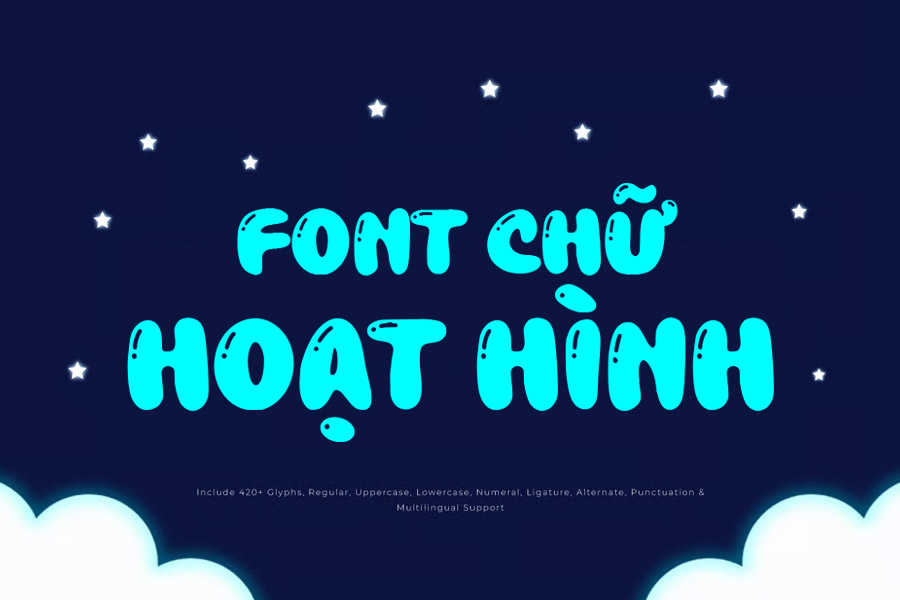
2. Vì sao nên chọn font hoạt hình Việt hóa?
Sử dụng các font hoạt hình Việt hóa giúp bạn:
- Tránh lỗi hiển thị dấu tiếng Việt – nhất là trên Canva, PowerPoint, hoặc khi in ấn.
- Dễ dàng dùng trên mọi nền tảng thiết kế – kể cả với người không chuyên.
- Tăng sự chuyên nghiệp trong sản phẩm – từ menu nhà hàng trẻ em, đến banner lớp học.
- Mang lại trải nghiệm thị giác vui vẻ, dễ tiếp cận hơn với trẻ nhỏ.
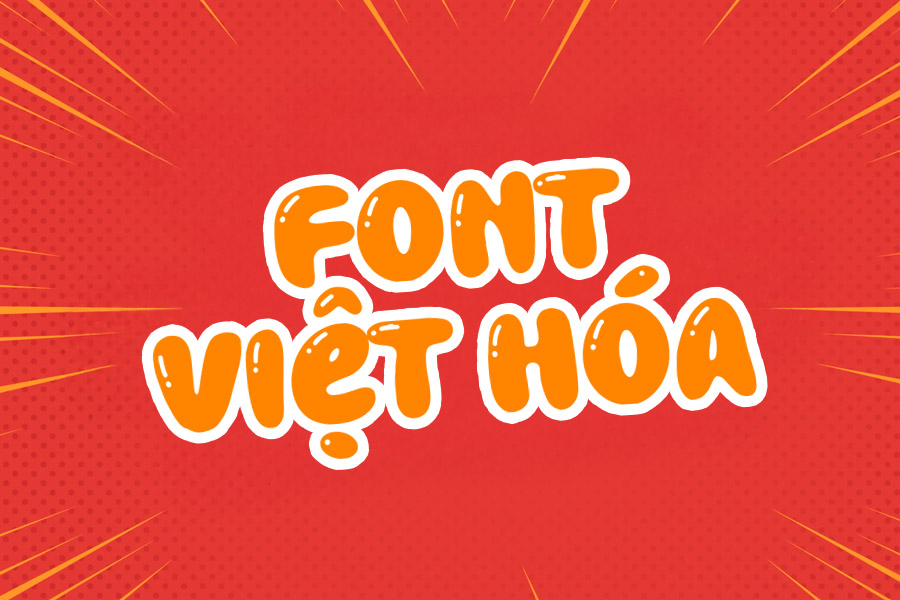
Top Font Chữ Hoạt Hình Việt Hóa Đáng Yêu Nhất 2025
FZ Brogles Trẻ trung và sinh động - Miễn Phí
Với đường nét bo tròn mềm mại, FZ Brogles đem lại cảm giác như bạn đang nhìn vào những quả bóng nước đang bật nhảy. Khoảng cách chữ rộng, nét vẽ dày vừa phải khiến font này đặc biệt dễ đọc – kể cả khi dùng làm tiêu đề hoặc in lớn. Một lựa chọn hoàn hảo cho áp phích lớp học, sách học từ vựng hoặc app thiếu nhi.
Tác giả gốc: Bangkit Tri Setiadi – thiết kế font "Brogles" được phát triển bởi Blankids Studio
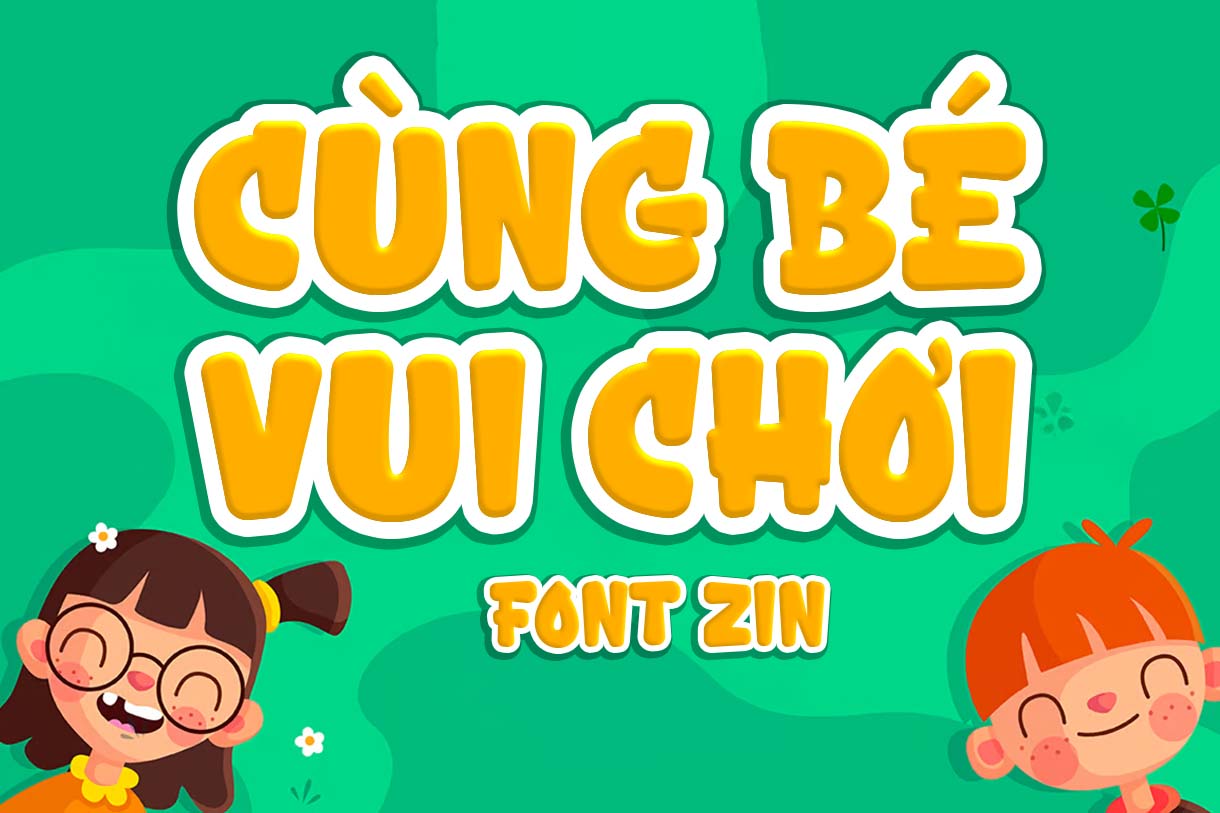
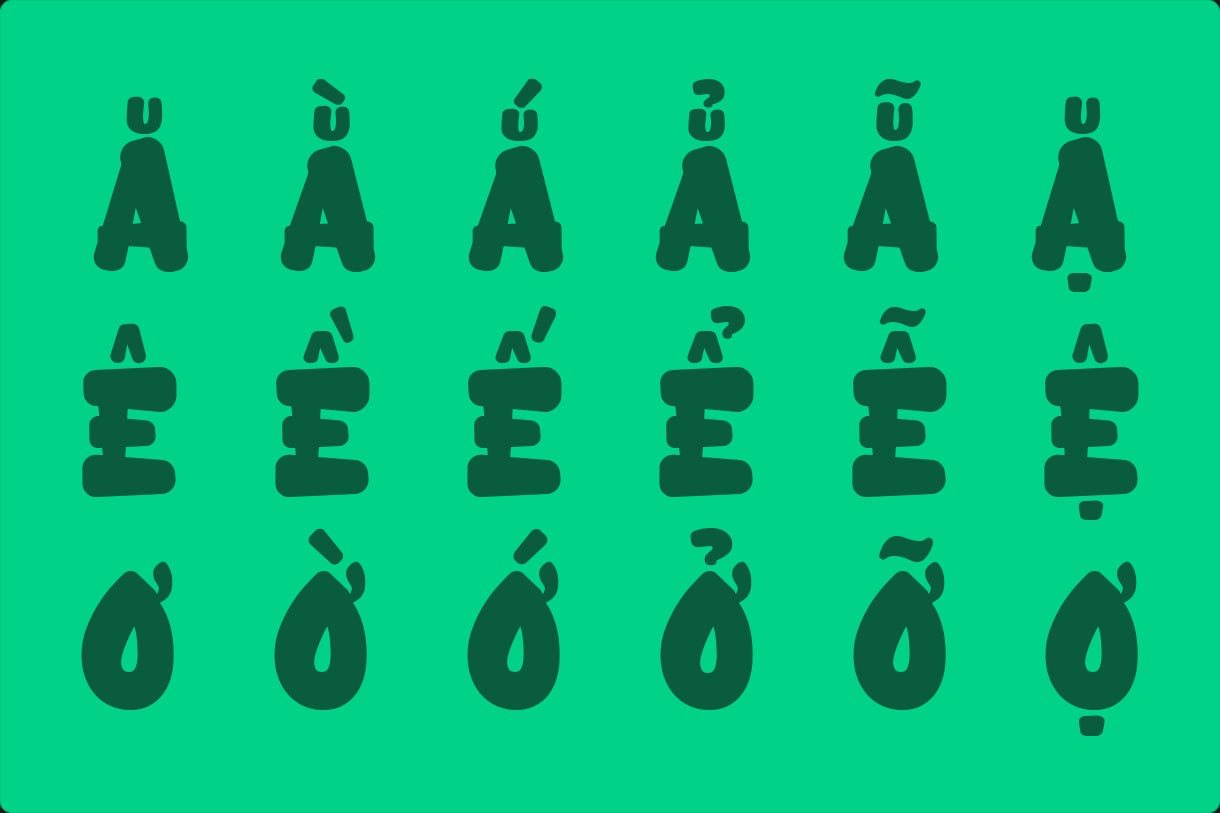
Font chữ TH Ekamai Béo tròn dễ thương
Nếu bạn đang tìm một font chữ béo tròn, bắt mắt và dễ dùng cho thực đơn trẻ em hoặc tiêu đề sách thiếu nhi, TH Ekamai sẽ khiến bạn hài lòng. Nét chữ đều đặn, bo tròn, dễ đọc ngay cả ở kích thước nhỏ. Cảm giác như từng ký tự được nặn từ bột bánh mềm, ấm áp.
Tác giả gốc: Dave Rowland (Eclectotype / Schizotype Fonts – ra mắt năm 2017)
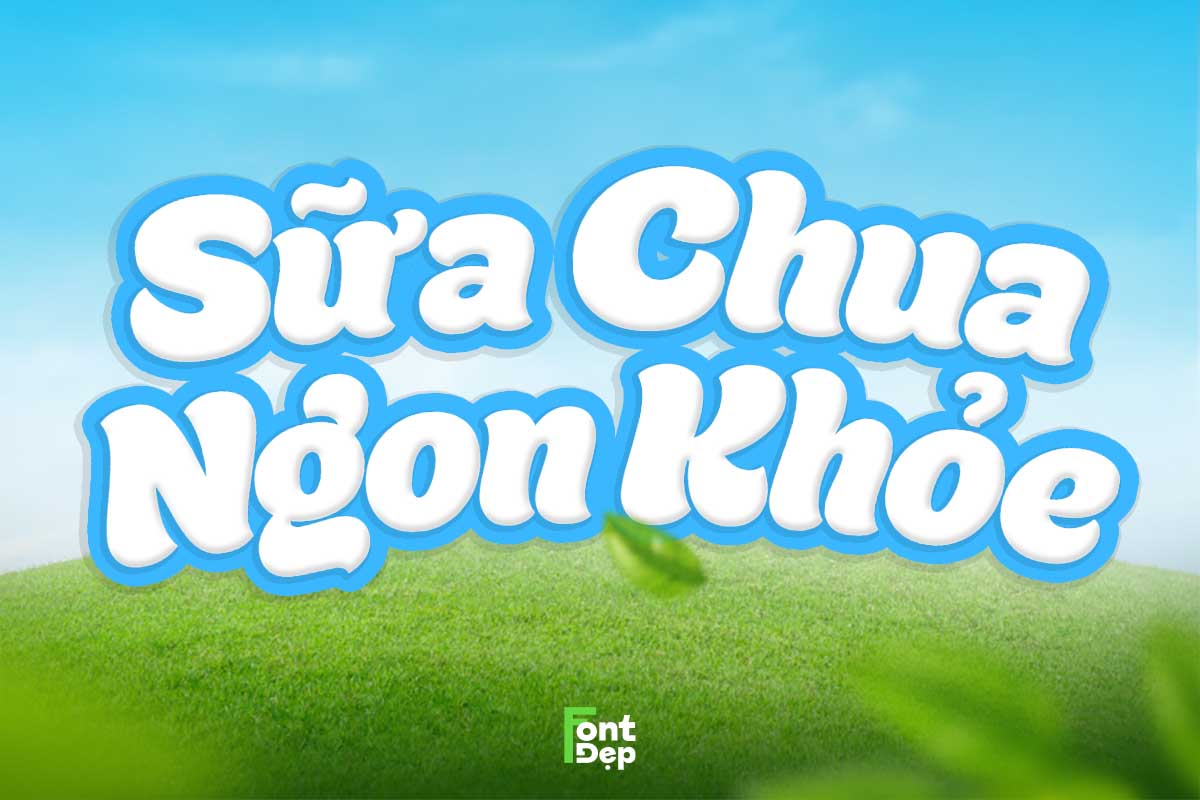
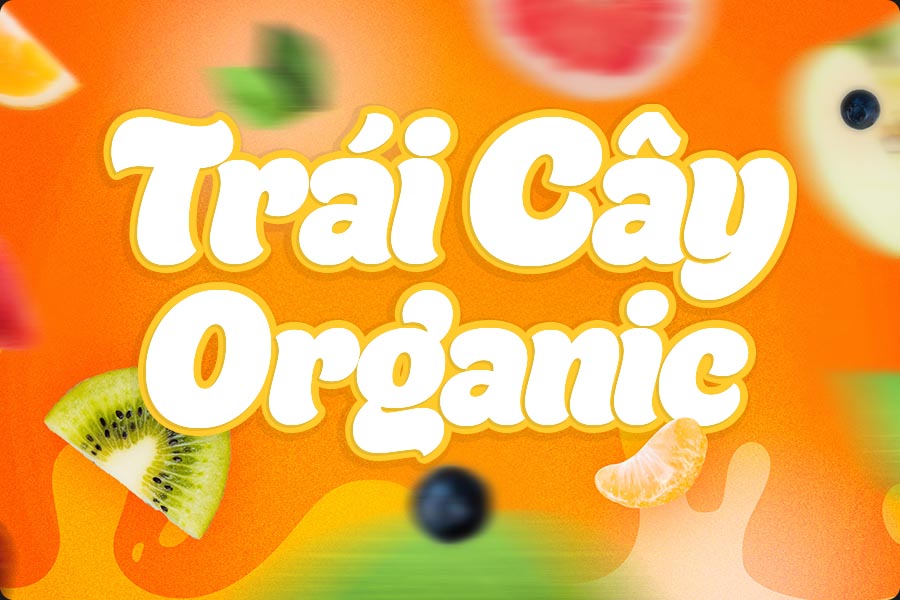
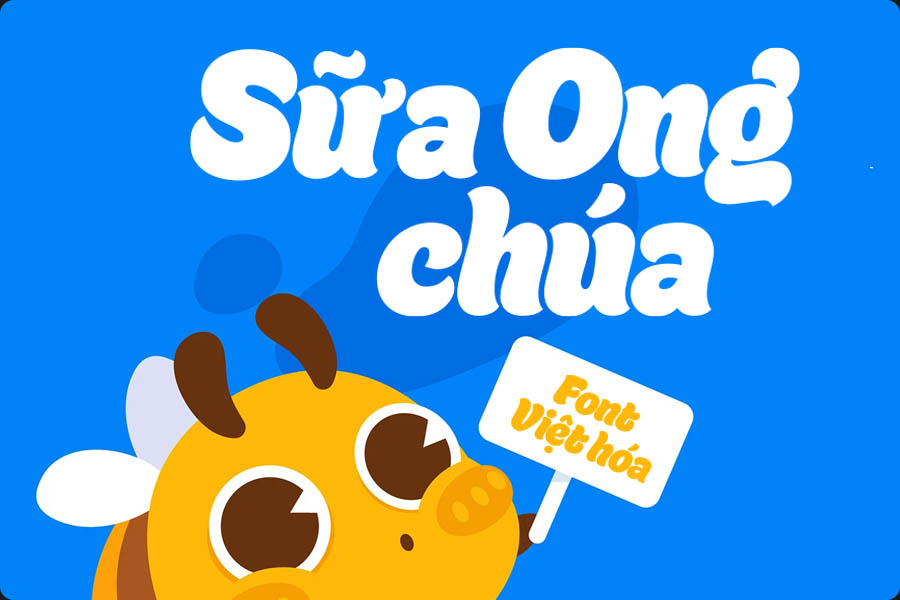
Font TH Mighty Kingdom mũm mĩm cute
Font chữ này khiến người ta liên tưởng đến các tựa game hoàng gia hoặc những câu chuyện cổ tích châu Âu. Nét chữ bo kỹ, chiều cao thấp, tạo sự cân đối và đáng yêu. Rất lý tưởng cho những sản phẩm hướng đến bé gái hoặc các app kể chuyện dễ thương.
Tác giả gốc: Alpaprana Studio (ra mắt vào năm 2021, miễn phí sử dụng cá nhân và thương mại)
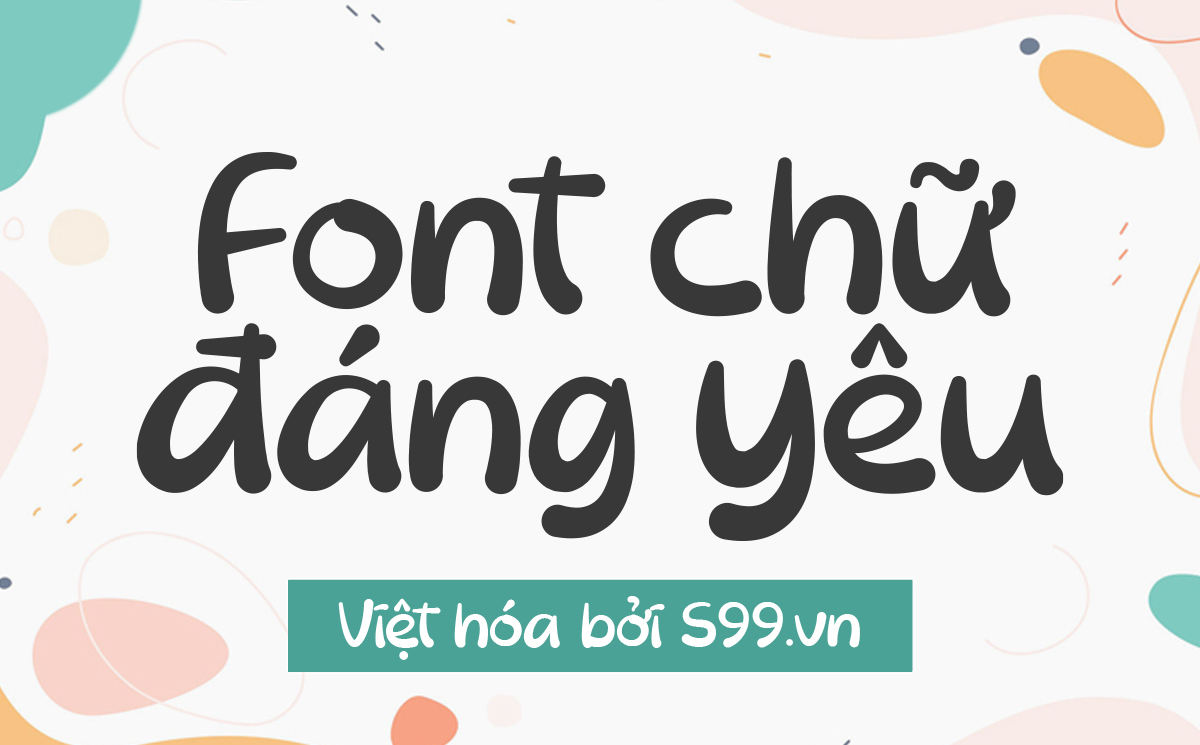
Font TH Monday Feelings Việt hóa – Nhẹ nhàng & thư giãn
Đúng như tên gọi, font này mang một năng lượng tích cực và dễ chịu. Đường cong mượt, tỷ lệ cân đối, rất dễ nhìn và phù hợp cho các thiết kế mang thông điệp yêu thương như thiệp sinh nhật, bảng quote hay bảng điểm thưởng của lớp mầm non.
Tác giả gốc: Essentials Studio (Thiết kế bởi Annas Rifky Anhar, ra mắt khoảng tháng 11/2022)
Việt hóa bởi: Phạm Sơn - Admin S99, Fontdep.vn
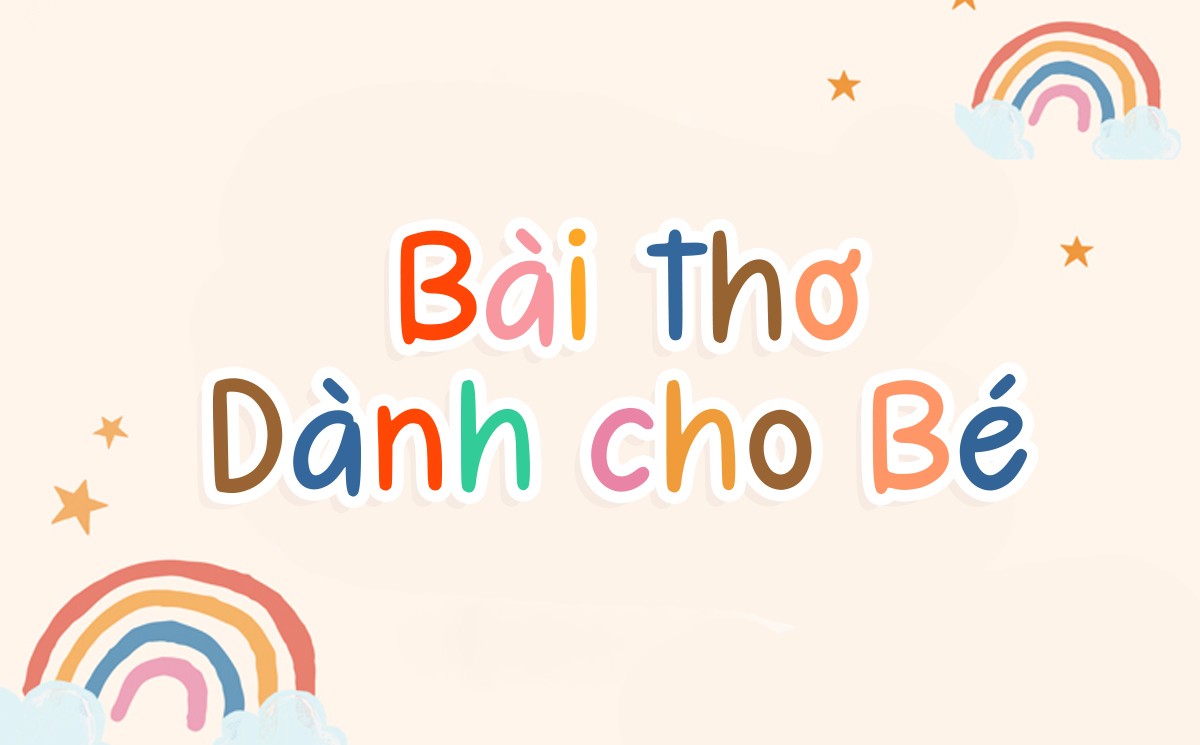
Font TH Cartoon 4 Việt hóa
Giống như những dòng chữ nắn nót trên bảng của cô giáo mầm non, TH Cartoon 4 có độ nghiêng nhẹ, nét cong tự nhiên nhưng vẫn rõ ràng và mạch lạc. Một lựa chọn tuyệt vời cho app học tiếng Việt hoặc sách luyện viết cho trẻ nhỏ.
Việt hóa bởi: Phạm Sơn - Admin S99, Fontdep.vn
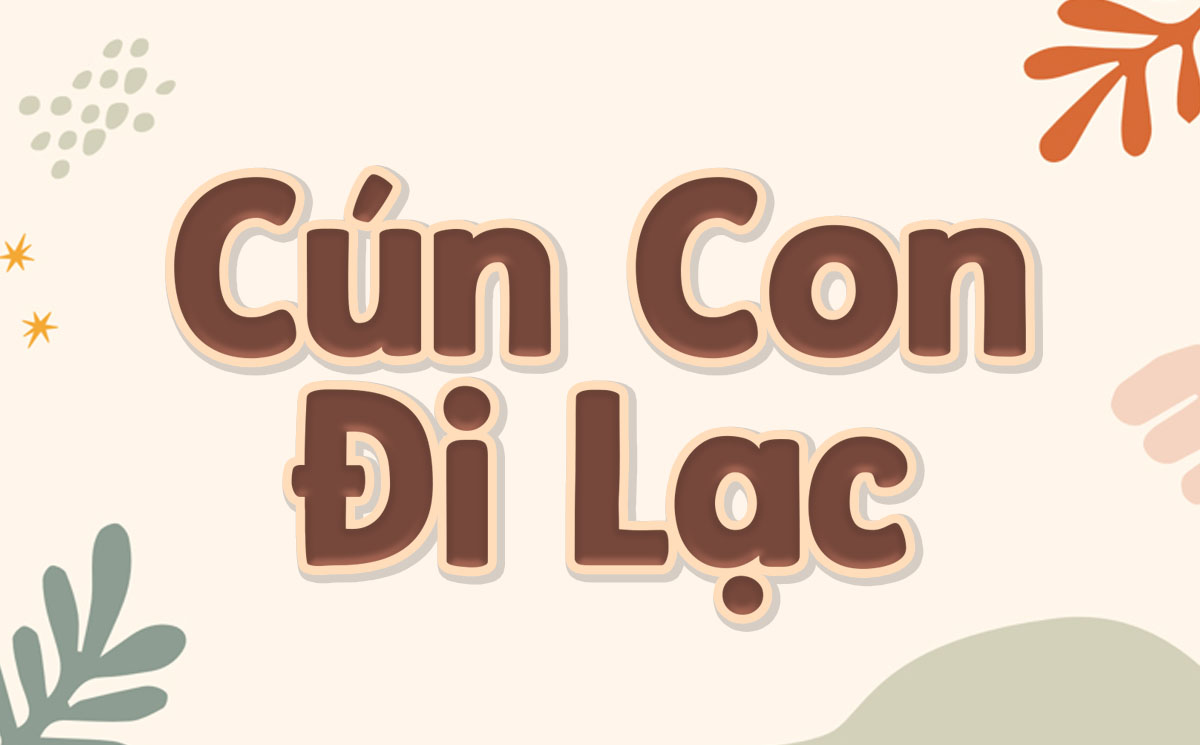
Font TH Grisly Beast Việt hóa – Béo tròn và vui nhộn
Lấy cảm hứng từ phong cách siêu anh hùng hoạt hình Mỹ, font này kết hợp giữa khối chữ dày, nét mạnh và độ dễ thương vừa đủ. Dùng font này cho poster truyện tranh, sách phiêu lưu hay các sản phẩm giáo dục STEM chắc chắn sẽ thu hút sự chú ý.
Tác giả gốc: Niskala Huruf (thiết kế phát hành năm 2022–2024, font hiển thị mạnh mẽ, vui nhộn, miễn phí thương mại)
Việt hóa bởi: Phạm Sơn - Admin S99, Fontdep.vn
Font chữ TH Choco Chici Việt hóa – Cute và đáng yêu
Từng nét chữ tan chảy như socola. Chiều cao thấp, bo tròn căng – cực kỳ phù hợp cho thiệp mời sinh nhật, bao bì bánh kẹo hoặc sticker dành cho bé gái. Nhìn thôi đã muốn nhón tay chạm vào.
→ Không hẳn. Font comic thường mạnh mẽ, đậm nét như truyện tranh siêu anh hùng, còn chữ hoạt hình thường mềm mại, dễ thương và phù hợp hơn với trẻ nhỏ.
Dùng font hoạt hình cho thương hiệu được không?
→ Có thể, nếu thương hiệu của bạn hướng đến trẻ em, giáo dục hoặc các sản phẩm vui nhộn.
Tôi nên chọn loại font cartoon nào?
→ Font béo tròn cho bé mầm non, font comic năng động cho app học tập, font trang trí cổ điển cho app kể chuyện.
Font chưa Việt hóa có vấn đề gì?
→ Dễ bị lỗi dấu, hiển thị sai ký tự trên phần mềm, gây khó khăn khi in ấn hoặc xuất bản.